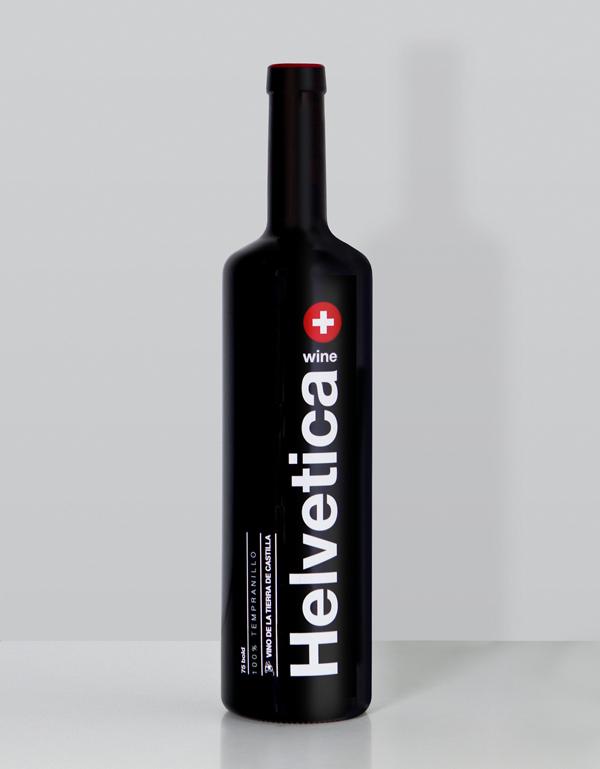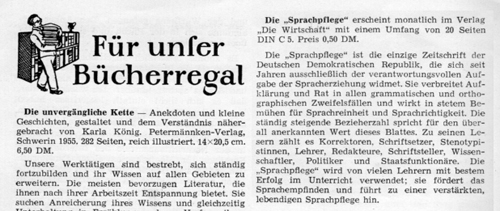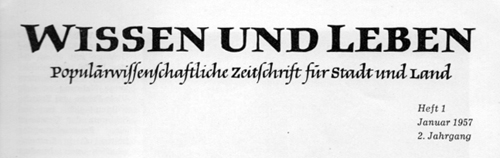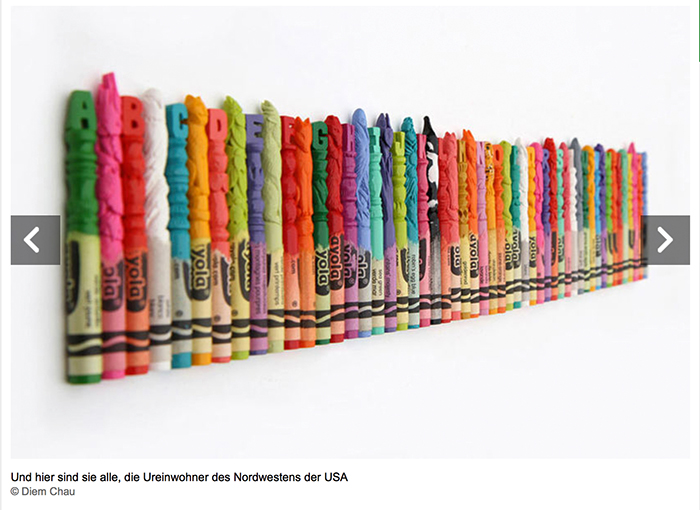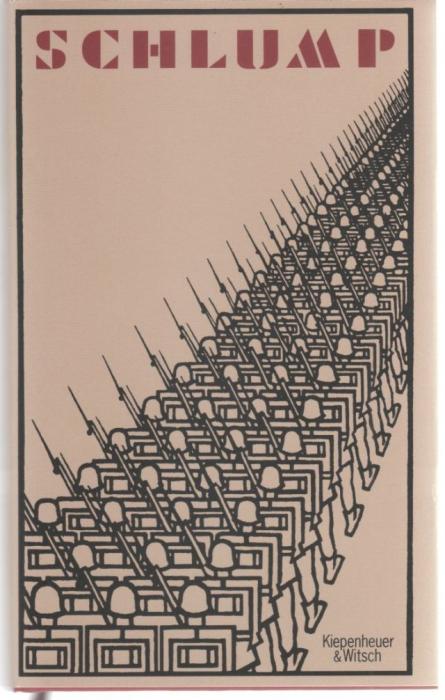
Besonders, wenn der Font gleich mit diesem schönen k ausgeliefert wird.
Ich bin tatsächlich mal gefragt worden, was den ein "Sekfaften" ist, und warum das erste f so seltsam aussieht.
Die Tierra de Castilla liegt in Spanien – was hat das mit der Helvetica und einer Schweizer Flagge zu tun?  :-?
Freu dich doch, dass die keinen Comic Sans-Wein keltern. :hammer:
Aber vielleicht ist der Winzer ja schweizer?
Meine Frau hat gerade einen Jahrgang vor dem Schredder gerettet und mir als Lektüre geschenkt. Es könnte eigentlich auch in „Geschichte“ oder „Welche Schrift ist das“.
Die beiden Scans zeigen die einzigen Stellen mit Lang-s.
Der Artikel rechts im zweiten Scan steht eigentlich am Fuß der Seite, da er aber thematisch ins Forum passt, habe ich ihn hochgeschoben.
Antikriegsroman von Hans Herbert Grimm aus dem Jahr 1928.
Wiederveröffentlicht 2014 unter Verwendung des Originalcover
von Emil Preetorius
Als ich das Buch in der Hand hatte (aufgrund seiner Geschichte neugierig geworden, hatte ich es mir gegönnt)* habe ich schon überlegt, wie man diese Graphik, die man heute am Rechner in ein paar Minuten fertig hätte, damals überhaupt so exakt hinbekommen hat. Gerechnet? Gemessen? Fluchtlinien gezogen und drauflosgezeichnet?
Mit Bleistiftminen hatten wir das Thema schon mal, hier kommen Wachsmalkreiden:
Fantastisches Alphabet – Orca, Fuchs und Schildkröte in Wachsmaler geschnitzt
Manche Menschen haben die Gabe, in alltäglichen Dingen Kunst zu sehen. Andere hingegen machen daraus Kunst. Für Diem Chau dienen Schulaccessoires als Inspirationsquellen - für ein neues Alphabet.